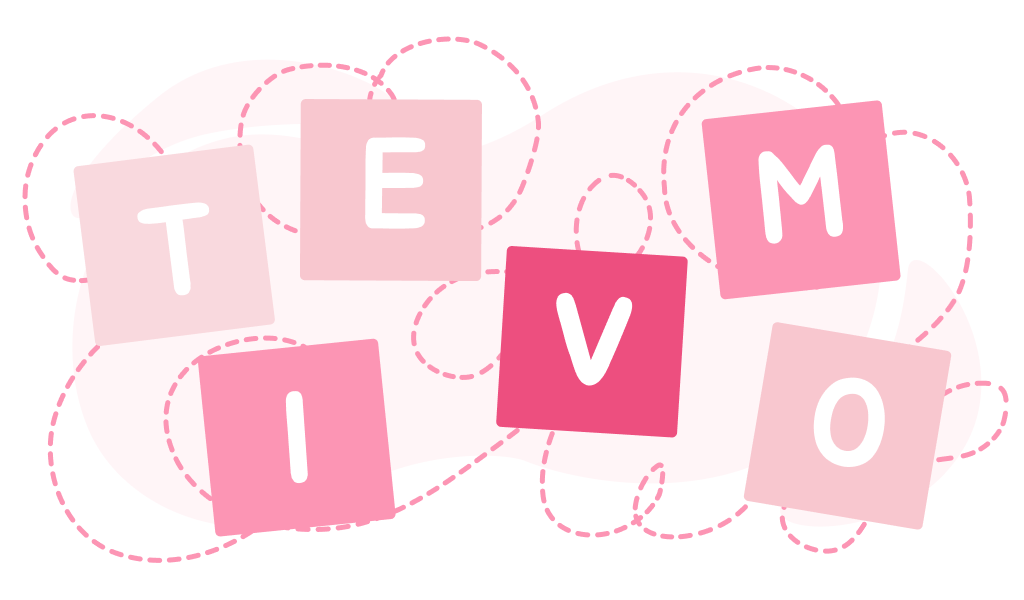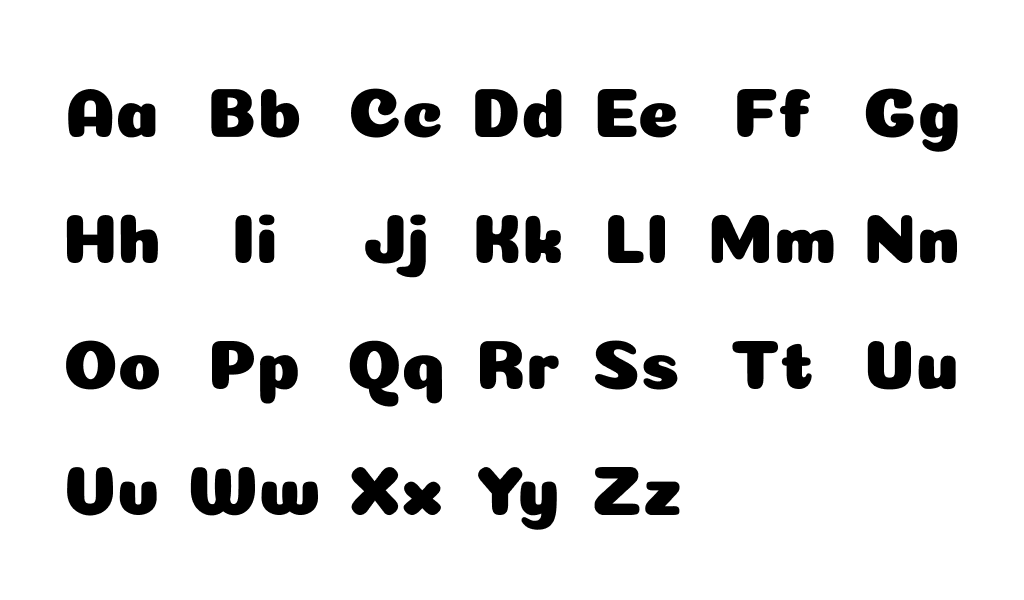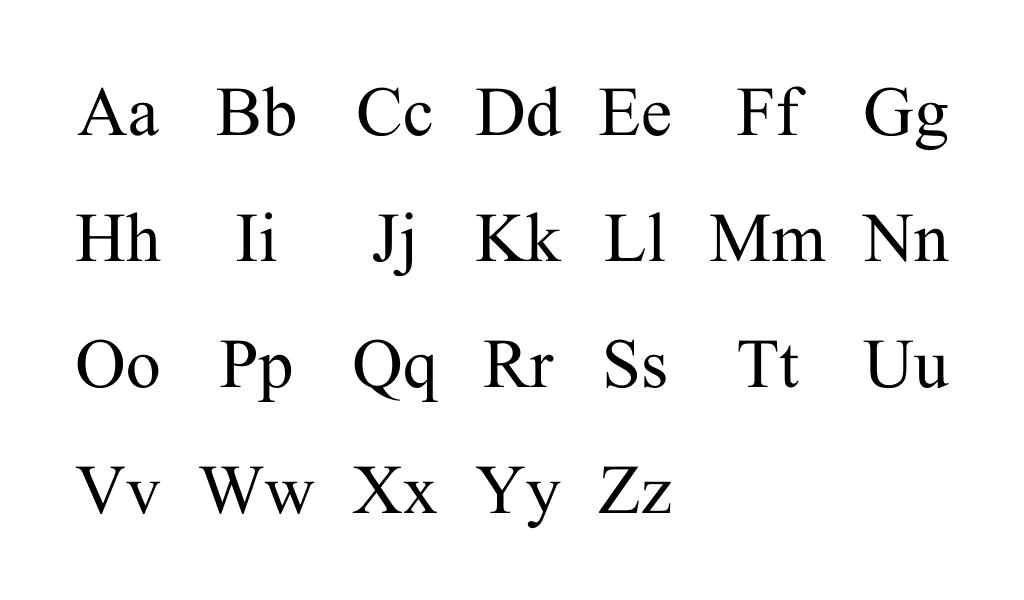
La tipografia esiste nell’umanità da centinaia di anni. Ognuno di noi entra quotidianamente in contatto con questo fenomeno, sfogliando il feed del proprio social network preferito, leggendo composizioni sulle etichette dei prodotti in negozio e guardando i cartelloni pubblicitari.
La tipografia è la progettazione visiva del testo, un elemento importante del marchio e una componente chiave della composizione.
La tipografia comprende molti aspetti: dall’impaginazione di giornali e riviste allo sviluppo di font per loghi. Con lo sviluppo del progresso tecnologico, ha cominciato a diffondersi ovunque: ora i suoi metodi e le sue tecniche sono utilizzati non solo nelle case editrici.
La tipografia moderna è “responsabile” non solo della leggibilità del testo, ma anche della sua progettazione grafica.
L’iscrizione dovrebbe evocare determinate associazioni ed emozioni nel lettore, stimolare azioni specifiche.
Prima di immergerci nell’affascinante mondo della tipografia, concordiamo alcuni termini. I termini “font” e “carattere tipografico” sono spesso usati in modo intercambiabile: questo non è del tutto vero. Un carattere tipografico è un insieme di caratteri, mentre un carattere è uno degli stili contenuti in un carattere tipografico.
Tutti i caratteri tipografici esistenti sono divisi in quattro tipi principali: antiqua, grottesco, scritto a mano e display.
Antiqua (noto anche come “stile umanista”) è un carattere tipografico con grazie, piccoli elementi che vanno oltre le componenti principali del carattere. Questo è uno degli stili più antichi e popolari e si ispira alla calligrafia tradizionale.
Si ritiene che l’antiqua sia apparso più di 600 anni fa. I caratteri serif sono un’opzione rigorosa e “formale” per i documenti formali. Si trovano spesso in pubblicazioni e documenti stampati. Questi caratteri hanno molte forme di esecuzione, possono essere in grassetto, corsivo, ecc. Lo stile serif più famoso è Times New Roman.
Il grottesco ha guadagnato popolarità relativamente di recente, a metà del 20 ° secolo. Dal suddetto stile umanista, si distingue per un aspetto gotico. Il carattere è considerato più moderno e chiaro, adatto ai testi elettronici: è facile da leggere sugli schermi. Questo carattere tipografico è una scelta eccellente per i titoli. Il suo “rappresentante” più famoso è il carattere Arial.
Il carattere tipografico scritto a mano è unico grazie alla sua maestria e alle sue curve aggraziate. Come il grottesco, il carattere manoscritto è apparso a metà del XX secolo. Il vantaggio dei caratteri scritti a mano è l’eleganza e la bellezza, lo svantaggio è che sono difficili da leggere: non tutti riescono ad analizzarli in modo semplice e veloce. La scelta di tali stili dovrebbe essere affrontata nel modo più responsabile possibile: il carattere dovrebbe attrarre, suscitare interesse e non respingere con la sua complessità.
Il carattere tipografico del display è il più insolito e informale di tutti. I caratteri sono molto originali, memorabili e creano uno stile unico. Queste opzioni saranno un’ottima opzione per titoli e loghi.
I caratteri tipografici si distinguono in un gruppo separato: sono utilizzati nei libri e nelle pubblicazioni online. Il loro principale vantaggio è che sono comprensibili anche in piccole dimensioni.
Elementi base della tipografia
Conoscere i componenti di base ti aiuterà a navigare meglio nella varietà di stili e a selezionare rapidamente ciò di cui hai bisogno.
Leader, leader: tutte queste sono designazioni dello stesso concetto: la distanza tra le linee. L’interlinea impostata correttamente rende il testo più leggibile. Se l’interlinea è minima, il testo diventa illeggibile ed estremamente difficile da leggere. Troppa distanza complica anche la percezione: è necessario attenersi alla “media aurea” e scegliere un valore medio (ad esempio, l’opzione “predefinita”).
La spaziatura delle lettere, o finale, è la distanza tra caratteri adiacenti. Una spaziatura troppo piccola tra le lettere crea un effetto di restringimento, troppa rende difficile separare una parola da un’altra. I parametri possono essere impostati manualmente: i programmi moderni offrono questa opportunità.
La crenatura regola la spaziatura tra le lettere solo all’interno delle parole: i valori non si applicano a tutto il testo. Molto spesso, questo strumento viene utilizzato quando si disegnano loghi: consente di implementare idee stilistiche insolite.
Un grafema è la più piccola unità di testo: un simbolo (lettera, numero, segno di punteggiatura).
Kerning, tracking e leading: cosa significano?
Kerning = spazio tra coppie di lettere; tracking = spaziatura uniforme del testo; leading = interlinea tra righe.
Cos’è la x-height e perché è importante?
È l’altezza delle minuscole senza ascendenti/descendenti; più è generosa, più migliora la leggibilità su schermi piccoli.
Come scegliere e abbinare i font per brand e sito?
Definisci un primario coerente col tono e un secondario complementare; cura contrasto, gerarchie, licenze e test su mobile/dark mode.